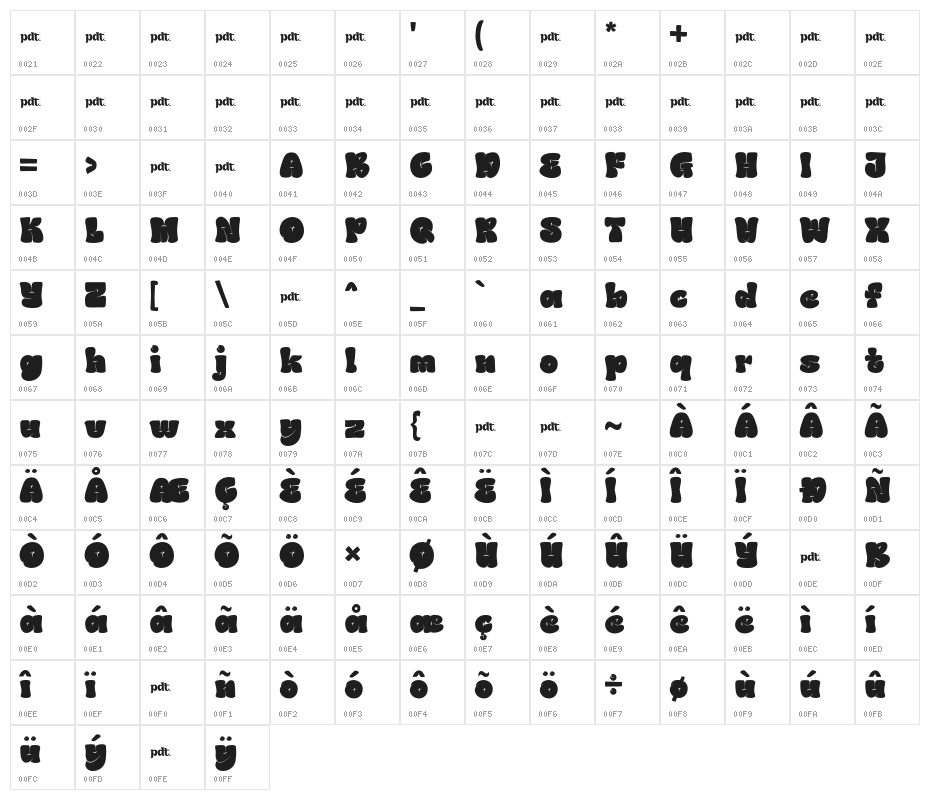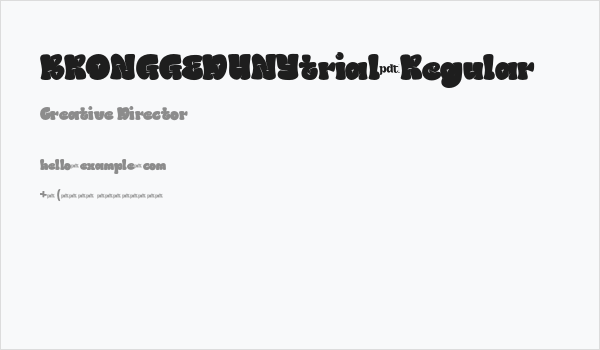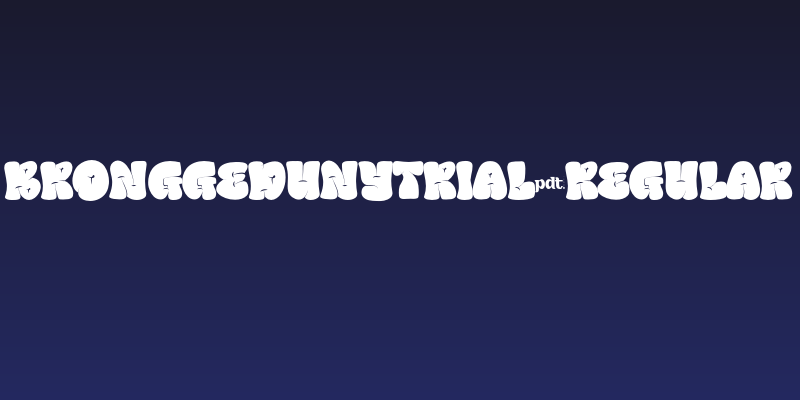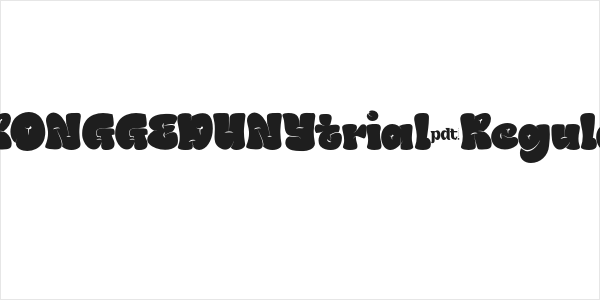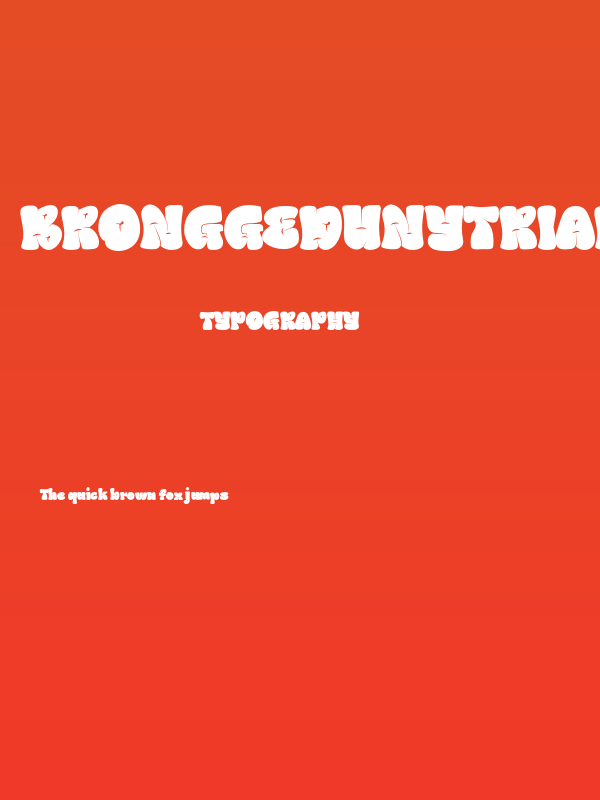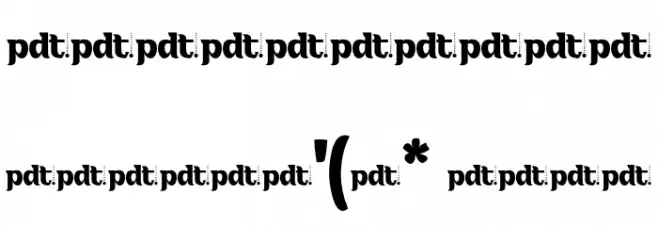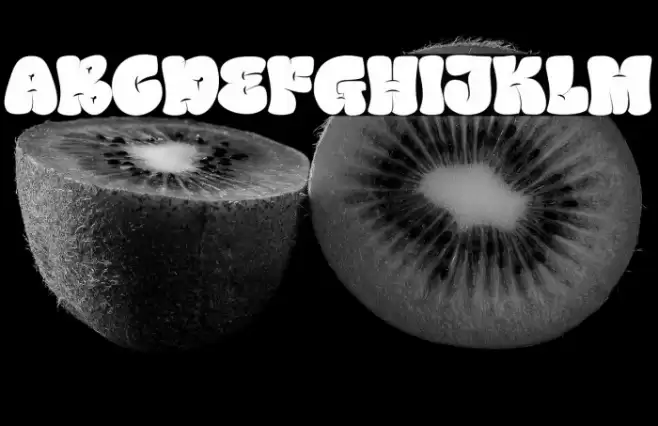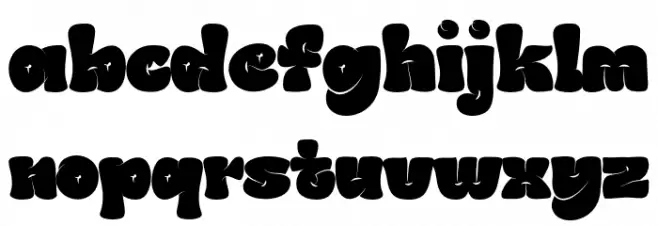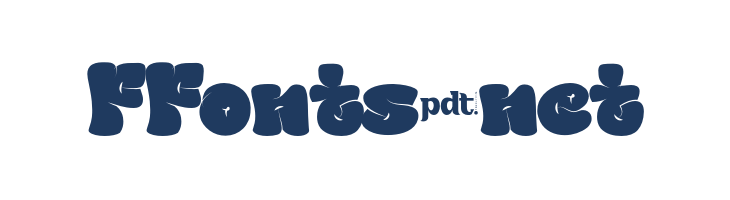
BRONGGEDUNYtrial-Regular Font
| Famiglia di caratteri | BRONG GEDUNYtrial |
| Stile generale | Playful, Bold, Friendly |
| Progetti proposti | Ideal for children's books, playful branding, posters, and any design requiring a fun and bold typeface. |